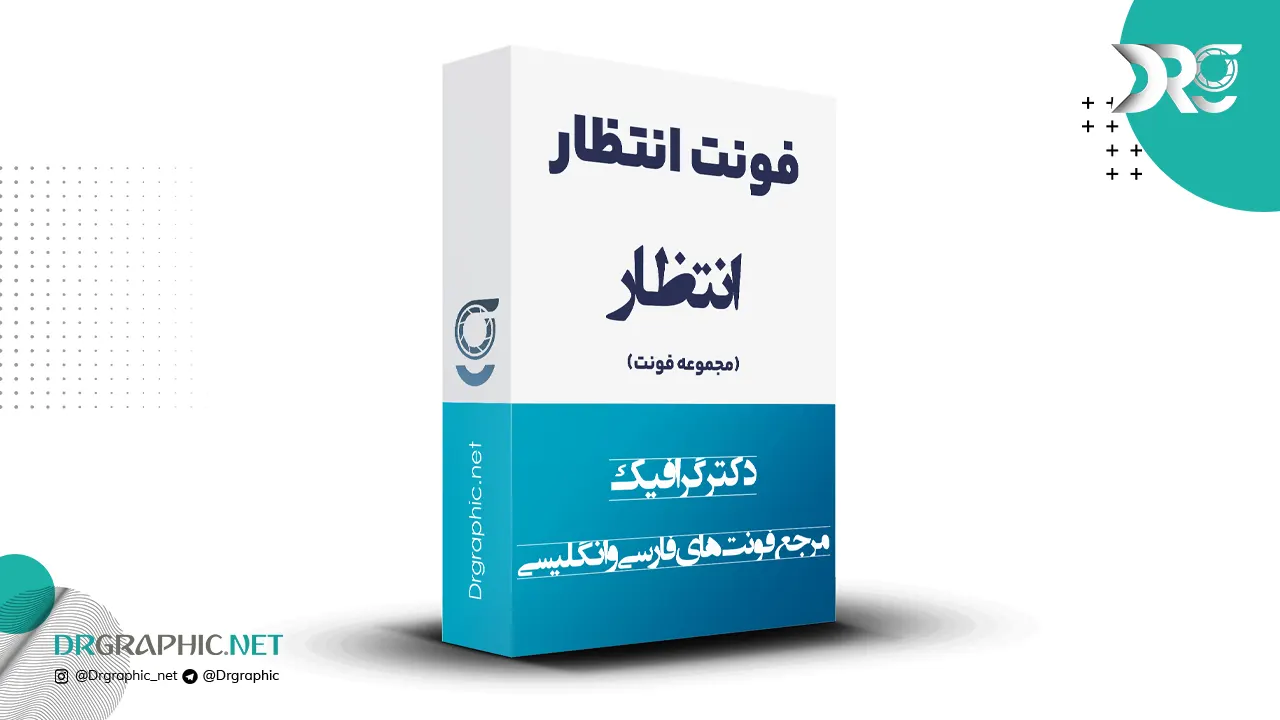
دانلود فونت فارسی انتظار Entezar 2
فونت انتظار ظهور نام یک مجموعه جدید و فوق‌العاده زیبا از قلم‌های فارسی می‌باشد که در 18 سبک مختلف برای شما طراحان و علاقه‌مندان به دنیای گرافیک آماده شده است. فونت انتظار ظهور ، یک مجموعه بسیار زیبا و کم‌نظیر در میان فونت‌های فارسی زبان است که با دارا بودن سبک‌های متنوع و زیبا، از آن‌ می‌توان طرح‌هایی زیبا و دیدنی را خلق کرد.
نمونه نوشته با این فونت: